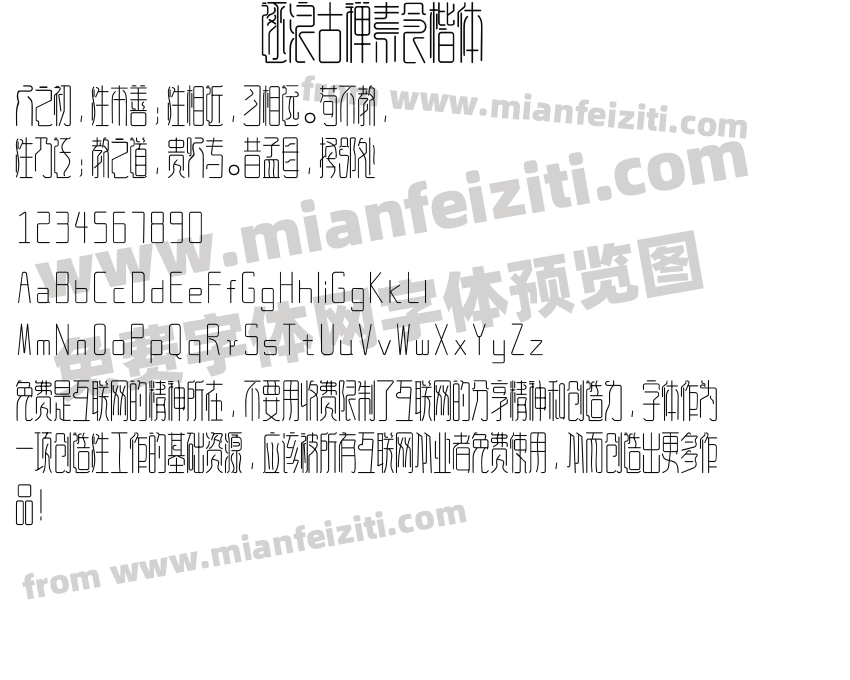
逐浪古禅素食楷体,是一款优秀的瘦长中文字库,传统字库都是基于近似方正的形状造型,使字体效果过于雷同。
本字库则进行了全新的模板校定,即实现了长方形的构字,同时又能在所有软件中实现严谨的布局(即自动行高、字距亦以长方形紧密藕合)。
字体取细、取古,以中文简体字为标准,融入逐浪生僻字库和矢量图标库支持,是艺术设计、文档制作、图形展示的优秀必选。